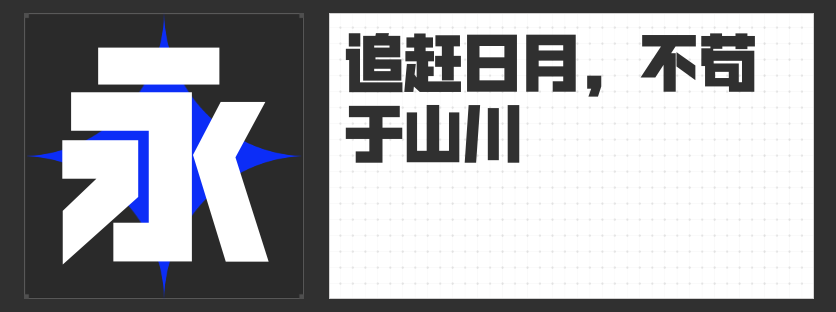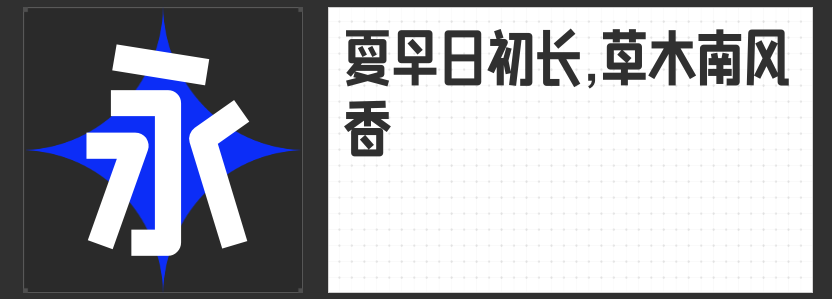
海报设计字体指南:四款吸睛利器打造视觉焦点
在海报设计的方寸之间,字体不仅是信息传递的载体,更是视觉张力的核心引擎。以下四款风格迥异的字体,从现代极简到传统写意,从力量感爆发到柔美灵动,为不同主题的海报提供精准表达方案。
1.励字开拓者简 超黑
这款字体以绝对理性的姿态重构汉字美学,横平竖直的直线系统构成精密网格,平切起笔与镜像化处理消解传统书法曲线。超黑字重搭配方正骨架,在科技展会海报中可强化未来感,而网红生僻字的完整支持,更让节日营销海报轻松实现文化破圈。当需要传递"硬核""极简"等概念时,它便是最直接的视觉语言。
2. 造字侠伏魔简繁 传神
泼墨书法的动态韵律被凝练成视觉符号,夸张的勾挑笔画如利剑出鞘,粗细对比形成戏剧性张力。这款字体自带武侠片场特效,适用于动作电影海报、电竞主题设计,或需要传递"力量""对抗"等激烈情绪的场景。传统书法韵味与现代设计语言的碰撞,让文字成为自带BGM的视觉武器。
3. 造字侠醉春风简繁 苍劲
圆润点画与自由笔画走势,将毛笔的呼吸感注入数字字体。这种松弛而不失法度的设计,完美适配文艺展览海报、书店活动主视觉,或需要传递"温暖""文艺"气质的设计需求。当海报需要打破刻板印象,营造轻松愉悦氛围时,这款字体便是最佳的视觉调酒师。
4. 创客贴夏至体
修长比例与清秀骨架,让文字如舞者般舒展。这款字体专为时尚品牌海报、美妆产品推广而生,其纤细而不失力道的特质,能精准诠释"精致""优雅"等女性向主题。在需要营造高端质感或留白意境的设计中,创客贴夏至体将以最少的视觉占位,传递最精准的格调暗示。
四款字体如同设计师的调色盘,既有理性至上的几何工具,也有情感丰沛的笔墨利器。它们突破汉字的传统表达边界,让海报设计在方寸之间完成从信息传递到情感共鸣的跃迁。无论是要制造视觉爆炸,还是传递细腻情愫,这些字体都是创意表达的完美拍档。